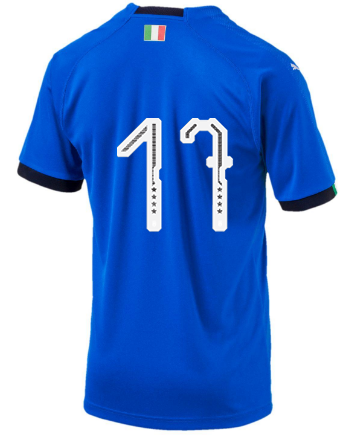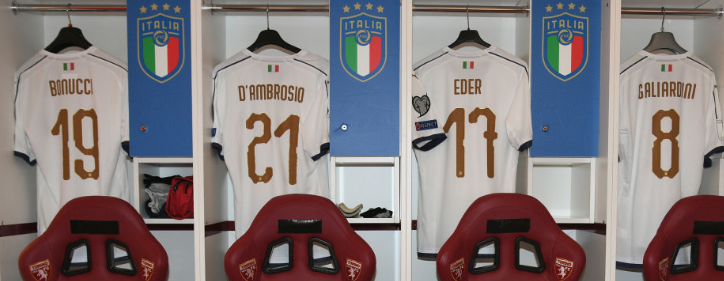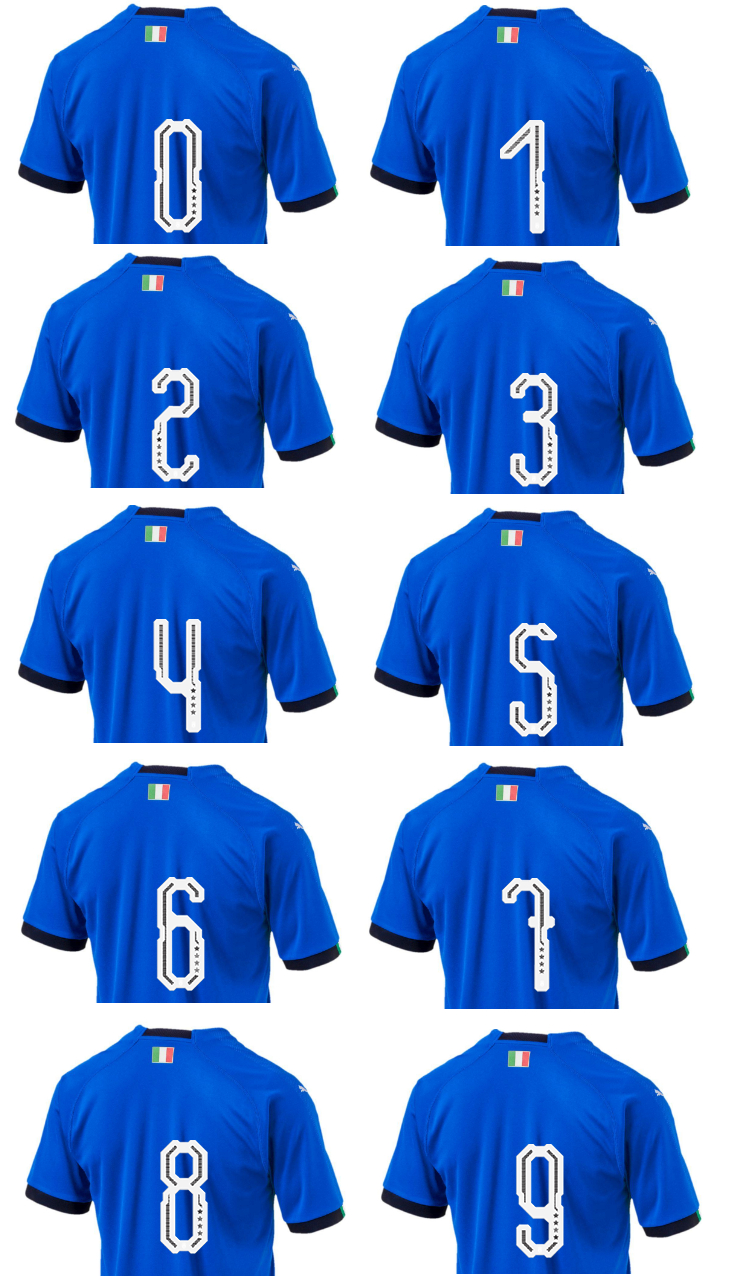
昨日発表されたイタリア代表の新たなユニフォーム。無事予選を突破したあかつきには、このワールドカップモデルでロシアでの戦いに挑むことになる。
すでに販売も開始されているのだが、公式オンラインショップでフォントを設定するとこんなことに!
かなり個性的だ。ちなみに、これは17番。
何と言っても特徴的なのは、4つの星がどの番号にも入っていること。
これは、新調された代表エンブレムでも強調されていた4度のワールドカップ優勝を表す星だ。
ただ、選手たちが実際に着用するものには★はなし。それでも、フォントの形は特徴的といえる。